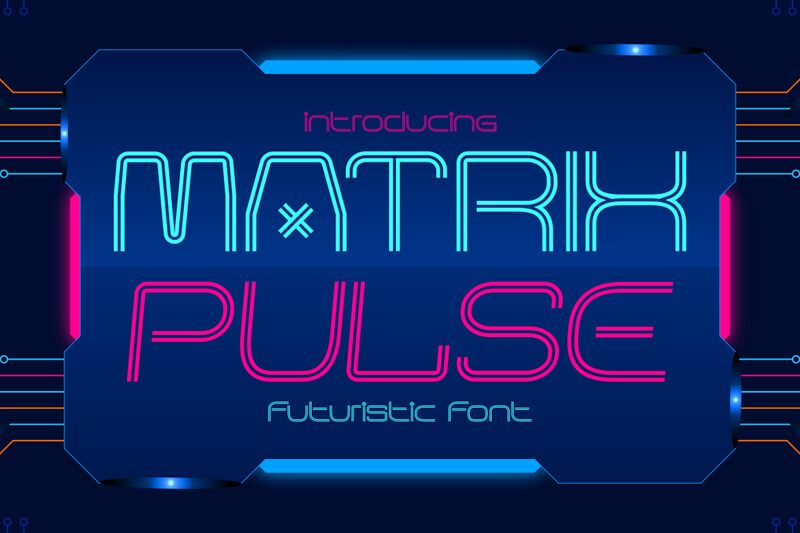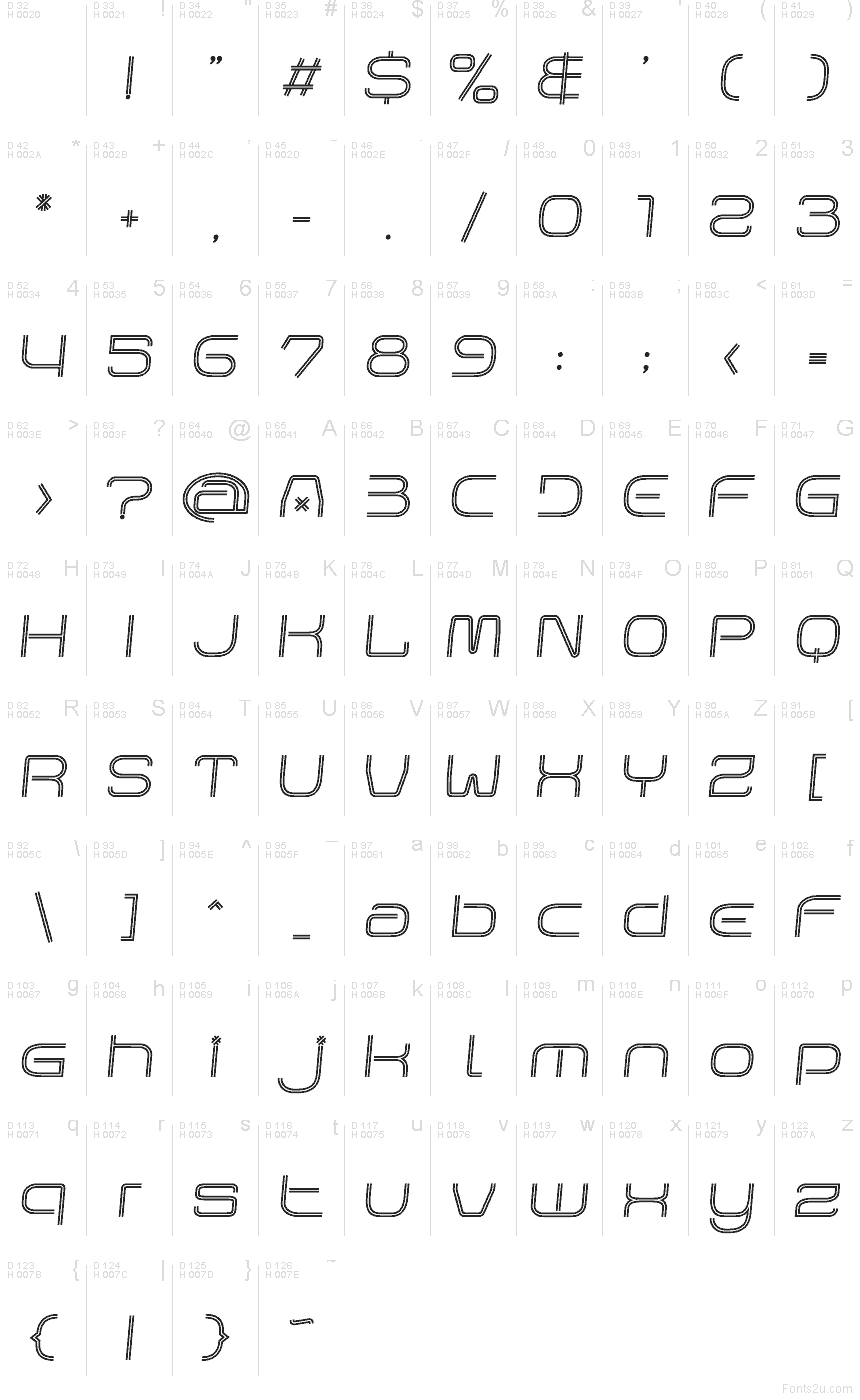
Matrix Pulse Slant
Matrix Pulse Slant von Shanaf Studio ist eine futuristische Display-Schriftart, die mit ihrem schnittigen, dynamischen Rhythmus überzeugt. Die Buchstaben basieren auf abgerundeten rechteckigen Formen und offenen Kurven, während die markanten, doppelten Umrisse dem gesamten Alphabet eine leuchtende, fast schaltungsartige Ästhetik verleihen – ideal für Techno-Signage statt klassischem Hard-Sci-Fi.
Sie passt hervorragend zu Postertiteln, Gaming-Grafiken, Musik-Covern, Event-Flyern und dynamischem Branding, bei dem eine futuristische, synthetische Stimmung gefragt ist. Perfekt geeignet für kurze Schlagzeilen, Titelkarten oder Logo-Designs, bei denen die mehrschichtige Kontur bereits ohne zusätzliche Effekte für starke visuelle Akzente sorgt.